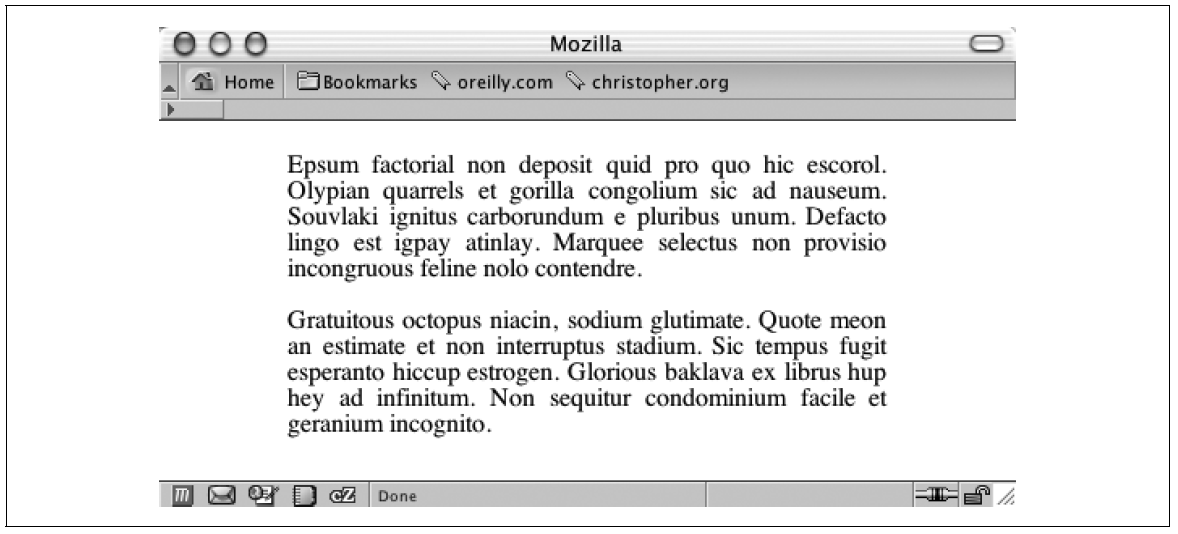
Text im Blocksatz darstellen
Problem
Sie wollen Text im Blocksatz, also gleichzeitig recht- und linksbündig darstellen, wie in der folgenden Abbildung gezeigt.
Abbildung: Der Absatz wird im Blocksatz dargestellt.
Lösung
Verwenden Sie die Eigenschaft text-align mit dem Wert justify:
P {
width: 600px;
text-align: justify;
}
Diskussion
Wie gut funktioniert die webbasierte Darstellung im Blocksatz? Gemäß der Spezifikation für CSS 2.1 hängt dies davon ab, welche Algorithmen die Browser-Entwickler verwenden. Da es hier keinen Standard gibt, unterscheidet sich die Blocksatz-Darstellung von Browser zu Browser, auch wenn der Blocksatz prinzipiell unterstützt wird. Folgende Browser bieten gute Unterstützung für text-align: justify;: Internet Explorer 4+ für Windows, Internet Explorer 5 für Macintosh, Mozilla Firefox 1.5+, Safari und Opera 3+. In diesen Browsern ist der Blocksatz gut zu lesen, in anderen Browsern sieht Text im Blocksatz vermutlich nicht so gut aus, weil durch die Darstellung zwischen den einzelnen Wörtern sehr viel Leerraum entstehen kann.